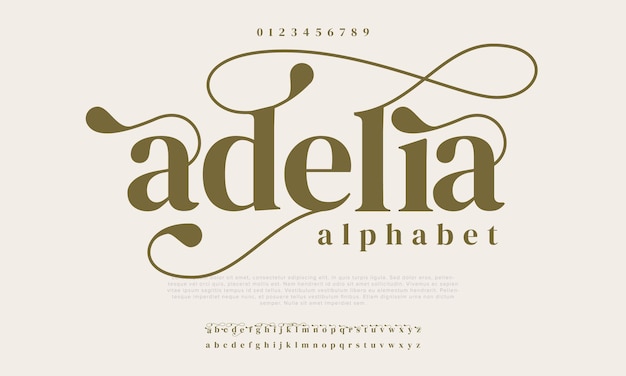
Police et nombre de lettres alphabétiques élégantes. Typographie Luxe classique lettrage polices serif mariage décoratif concept rétro vintage. illustration vectorielle